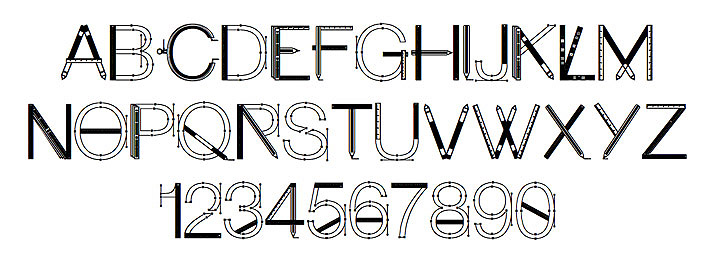
Una tipografía caracterizada por su gran geometría, formada por elementos que como reglas, compases o lápices, e incluso puntos de ancla a los cuáles los diseñadores estamos más que acostumbrados.
Ha sido diseñada por Yai Salinas, diseñadora argentina a la que le apasiona la geometría y es un elemento que siempre intenta incorporar en todos sus proyectos, como bien explica en su página web.
A typography characterized by its great geometry, formed by elements such as rules, compasses or pencils, and even anchor points to which the designers are more than accustomed.
It has been designed by Yai Salinas, an Argentine designer who is passionate about geometry and is an element she always tries to incorporate into all her projects, as she explains on her website.